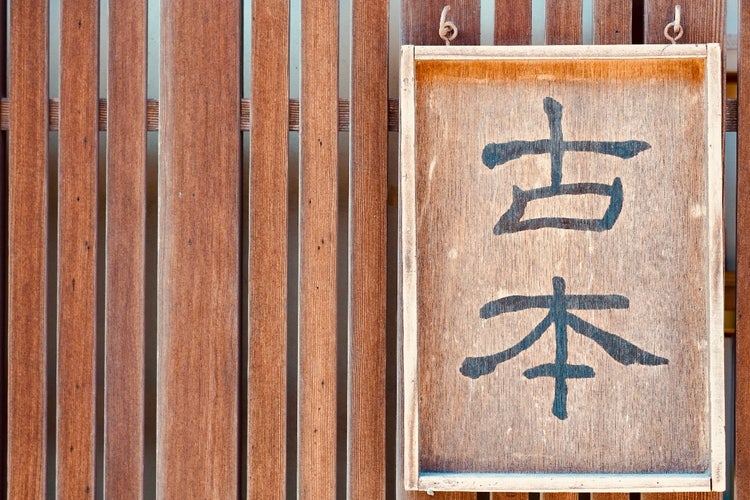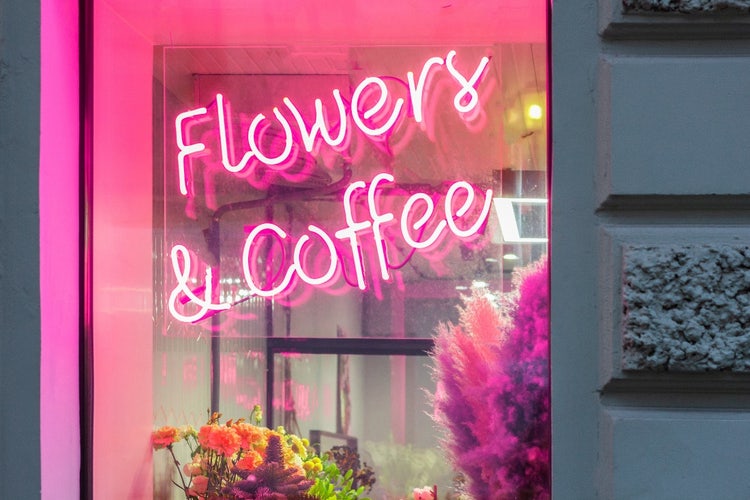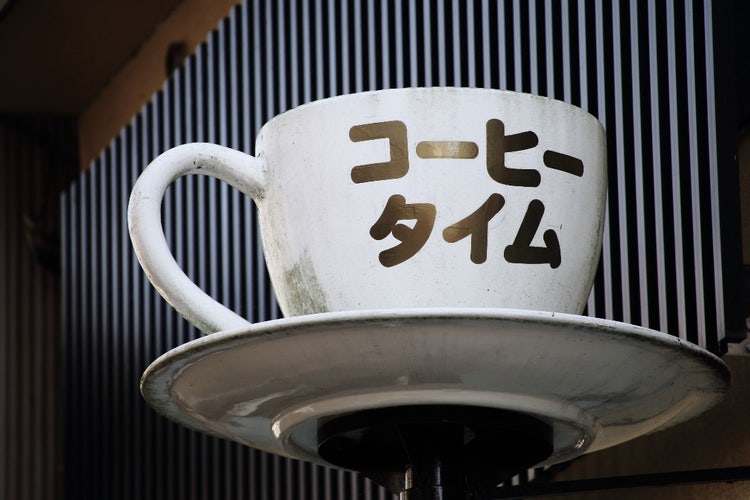
アドビは、4月10日のフォントの日を記念して「#私の推しフォント」を募集します。
身の回りにあるパッケージや看板など、味のあるフォントが使われている写真をTwitterに投稿してください。審査員に選ばれた投稿には賞品をプレゼントします。応募は2022年4月10日(日)のフォントの日当日のみとなるので、4月10日に向けてぜひ様々なフォントを集め、応募の準備をして下さい。同日13:00~15:00 CC道場にてフォントの日を盛り上げる配信企画も実施します。
投稿例
ポップで映えそうなカフェのネオン、思わずひと息つきたくなるような喫茶店のレトロなフォント、掘り出し物を見つけられそうな古本屋の味のある筆文字など、身の回りにある気になるフォント写真をぜひ投稿してみてください!